Inter là một bộ font sans-serif miễn phí, được phát triển bởi Rasmus Andersson nhằm tối ưu hóa việc hiển thị trên màn hình.
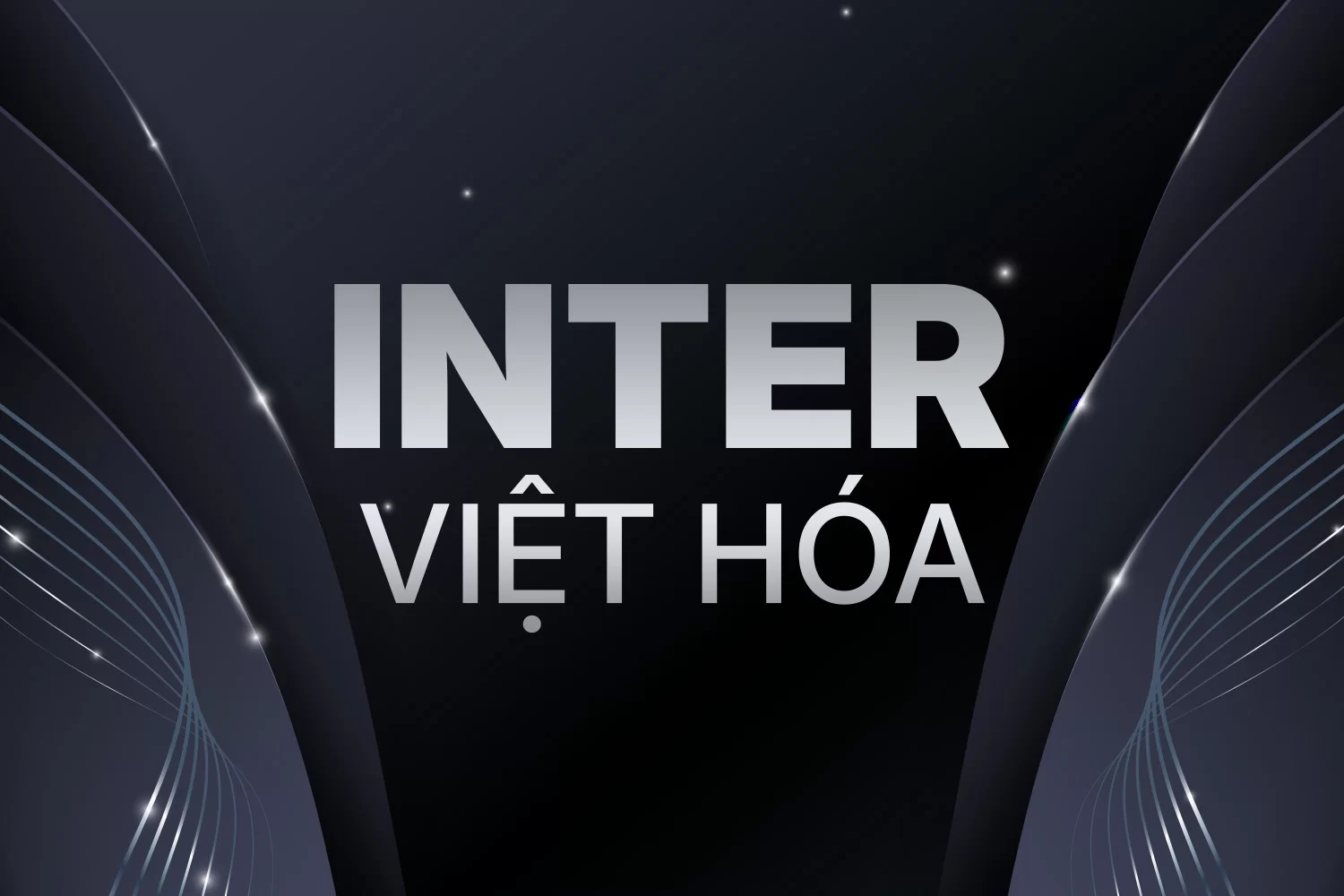
BD StreetSign Sans v2.0 là một font chữ hiện đại được tạo ra bởi Bún Đậu Foundry, lấy cảm hứng từ các bảng hiệu và biển báo đường phố.
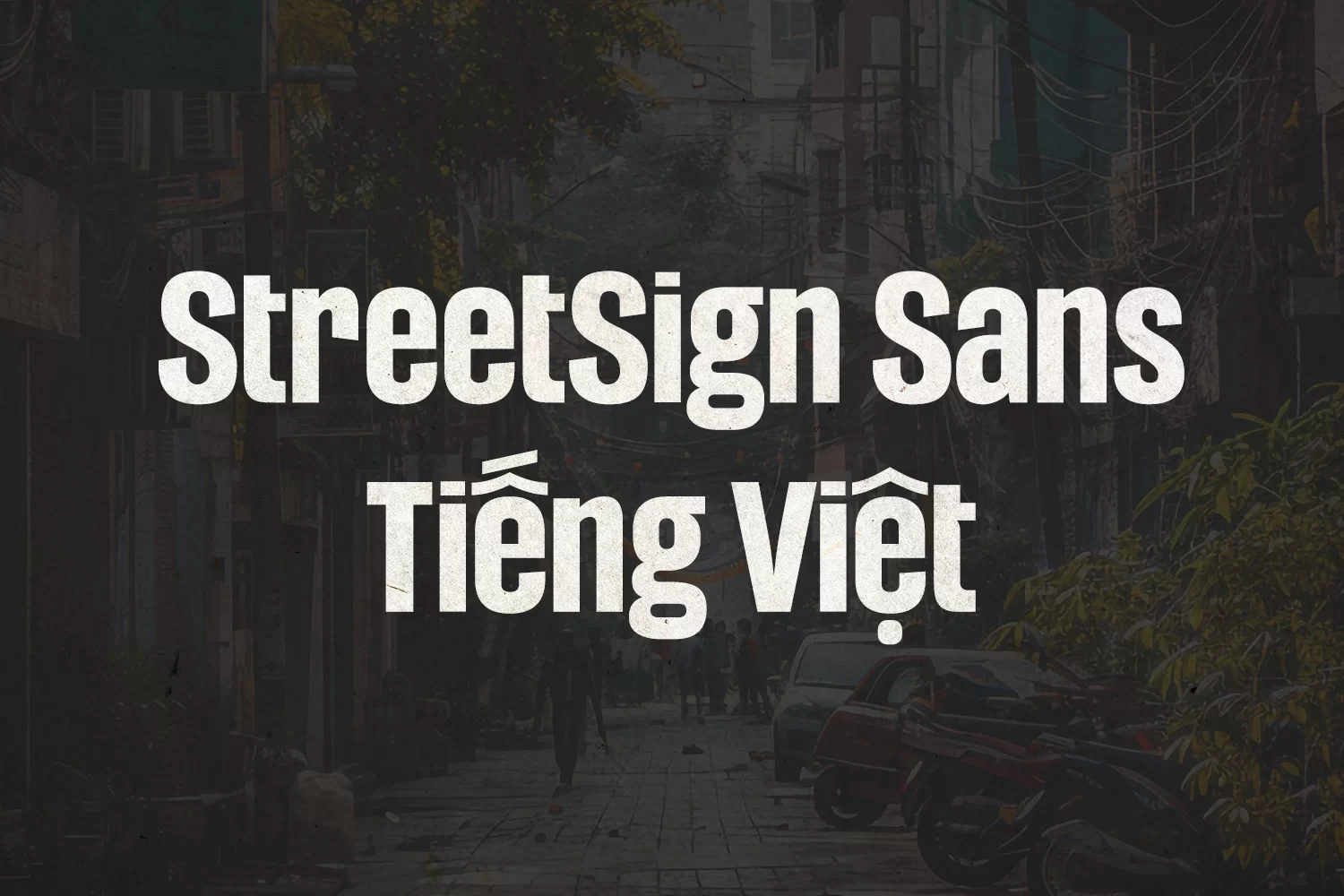
Fraunces là một typeface serif độc đáo kết hợp giữa cảm hứng cổ điển và yếu tố hiện đại, mang lại nét quyến rũ riêng biệt cho mọi thiết kế.
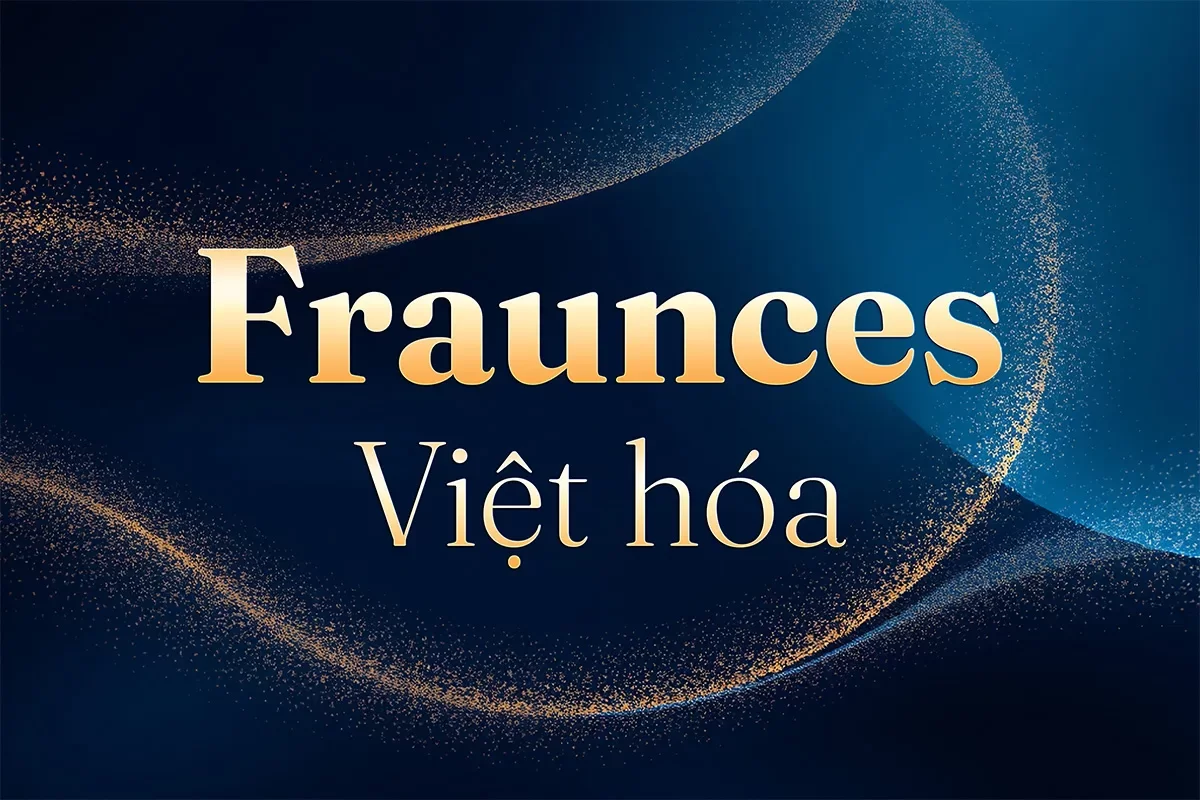
Font Meow Script Việt hóa mang đậm hơi thở của những dòng viết tay mềm mại, uốn lượn một cách duyên dáng như nét cọ trên giấy mịn. Từng ký tự được thiết kế với phong cách tự nhiên, dễ thương, rất phù hợp cho các dự án đòi hỏi cảm xúc nhẹ nhàng và gần gũi.
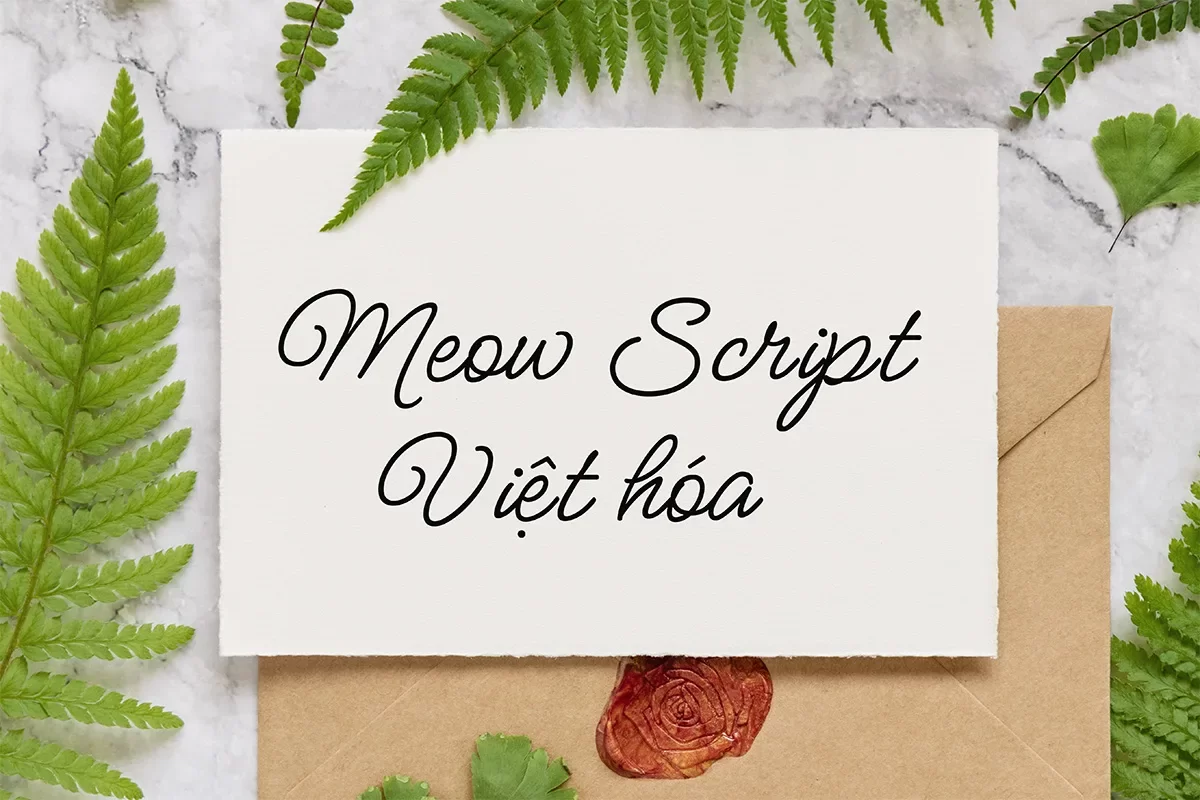
Wind Script Việt hóa là một kiểu chữ bay bổng mang phong cách thư pháp hiện đại, kết hợp giữa sự uyển chuyển tinh tế và độ tương phản mạnh mẽ.
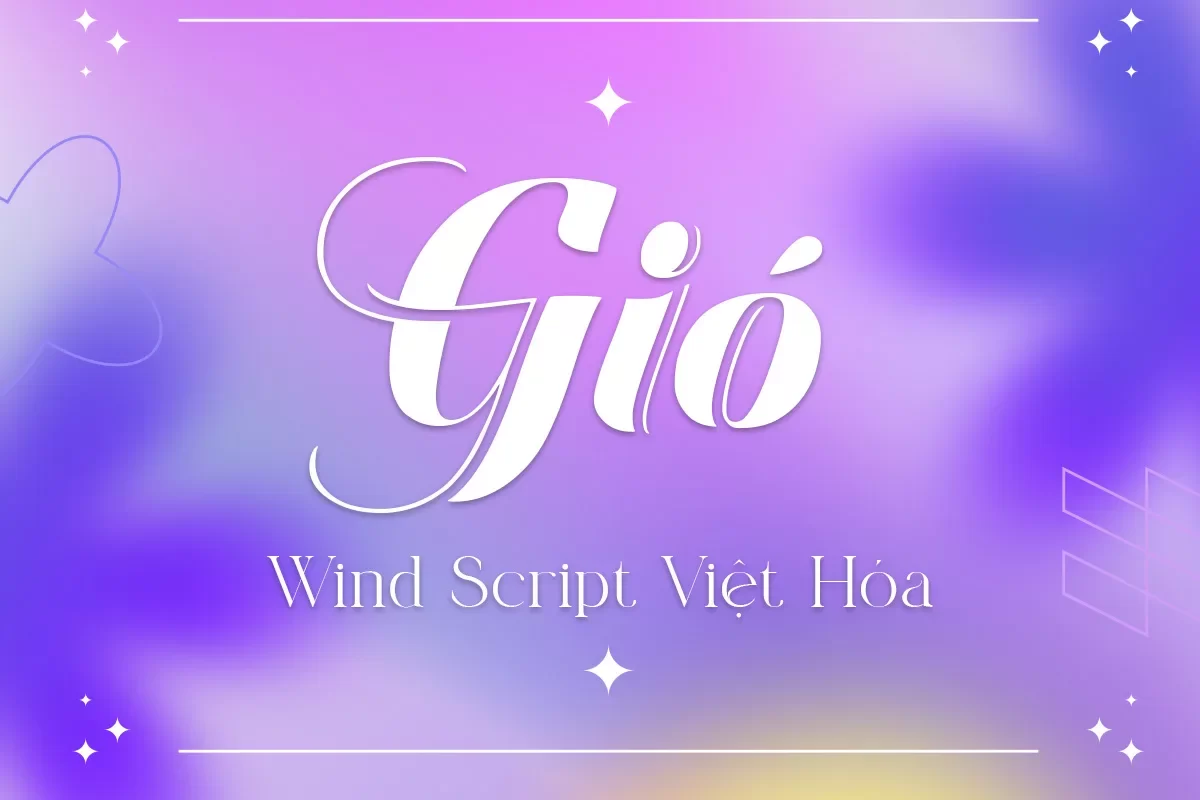
DVN – PoetsenOne Việt hóa là phiên bản Việt hóa của font PoetsenOne nổi bật trên Google Fonts, mang đến một phong cách đậm nét, bo tròn mềm mại và hiện đại. Với cấu trúc chữ cái chắc chắn và đầy đặn, font này truyền tải cảm giác thân thiện, dễ gần nhưng vẫn toát lên sự cá tính và nổi bật trong thiết kế.
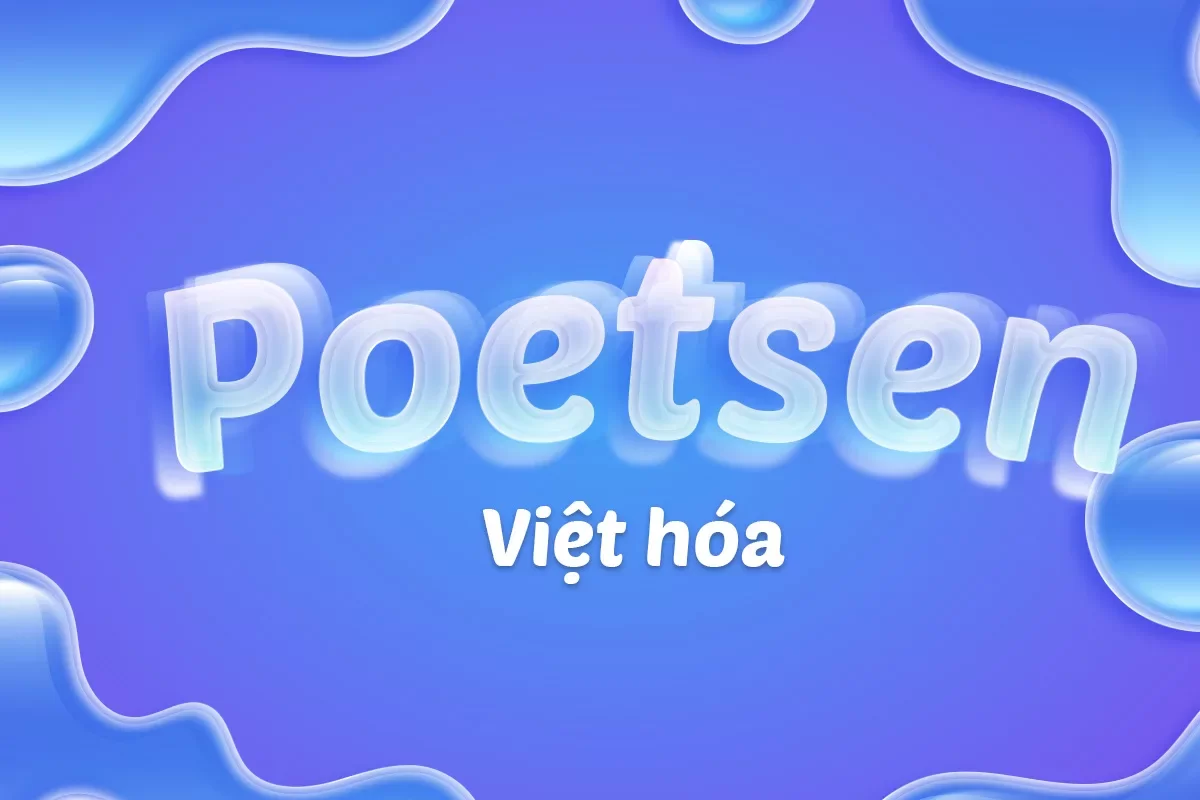
Font Play là một kiểu chữ sans-serif hiện đại, nổi bật với thiết kế tối giản và rõ ràng. Được tạo ra nhằm mang lại trải nghiệm đọc dễ chịu, Play có các đường nét thanh thoát, góc cạnh gọn gàng nhưng vẫn giữ được sự mềm mại ở các chi tiết bo tròn.
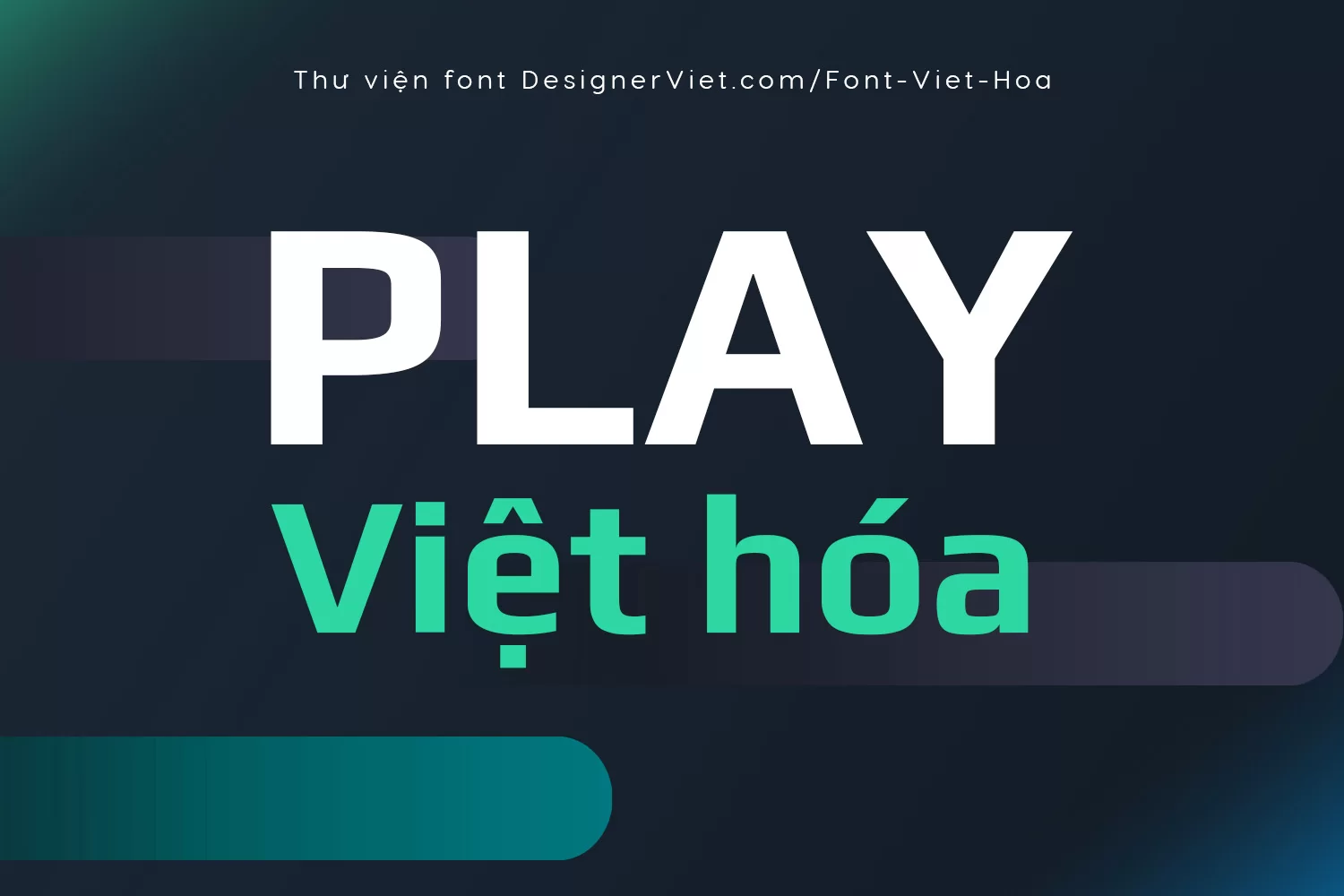
Hubbot Sans là một font chữ sans-serif hiện đại với các đường nét đơn giản và gọn gàng, lý tưởng cho các dự án cần sự rõ ràng và dễ đọc.
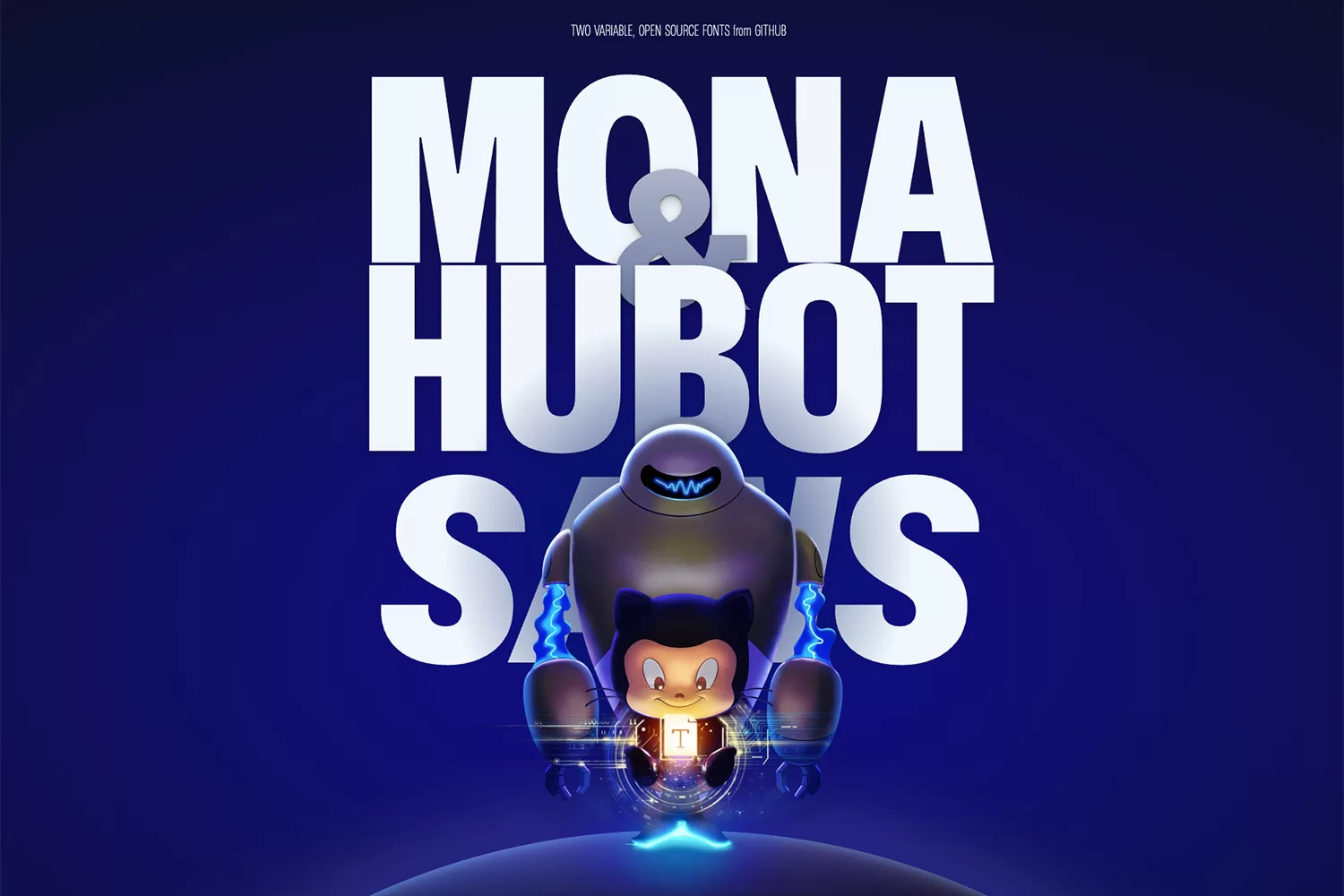
DVN Easter là một font chữ mang phong cách vui nhộn, sáng tạo, được thiết kế lấy cảm hứng từ những quả trứng phục sinh rực rỡ. Với các ký tự bo tròn, đáng yêu và các họa tiết trang trí bên trong, font này giúp bạn dễ dàng tạo ra những thiết kế ấn tượng cho các dự án lễ hội.
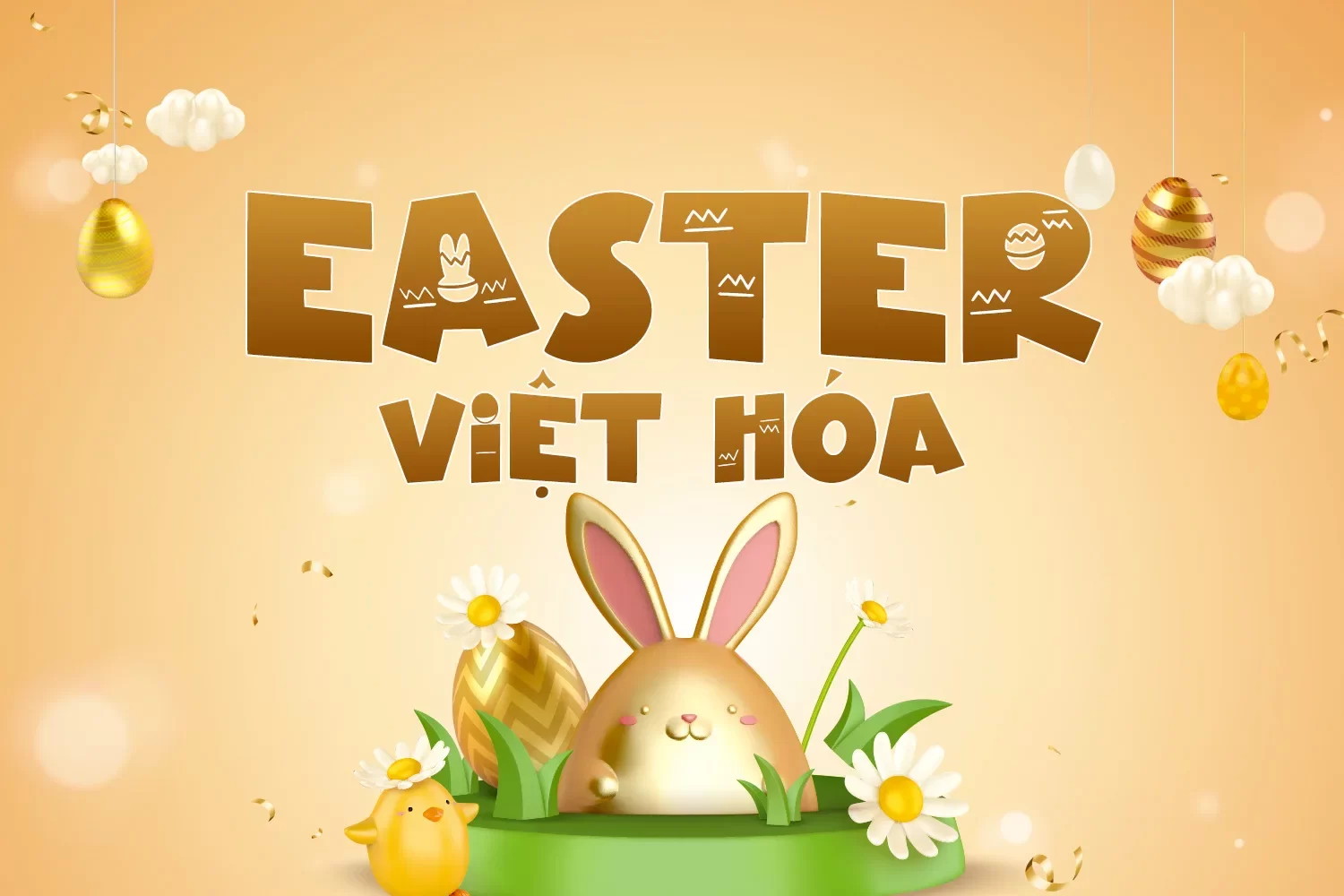
Fredoka One là một phông chữ được thiết kế bởi Atipo, một hãng thiết kế đồ họa đặt trụ sở tại Tây Ban Nha. Nó có phong cách đơn giản, vui nhộn và thân thiện, thích hợp cho việc sử dụng trong các dự án sáng tạo và giao diện người dùng.
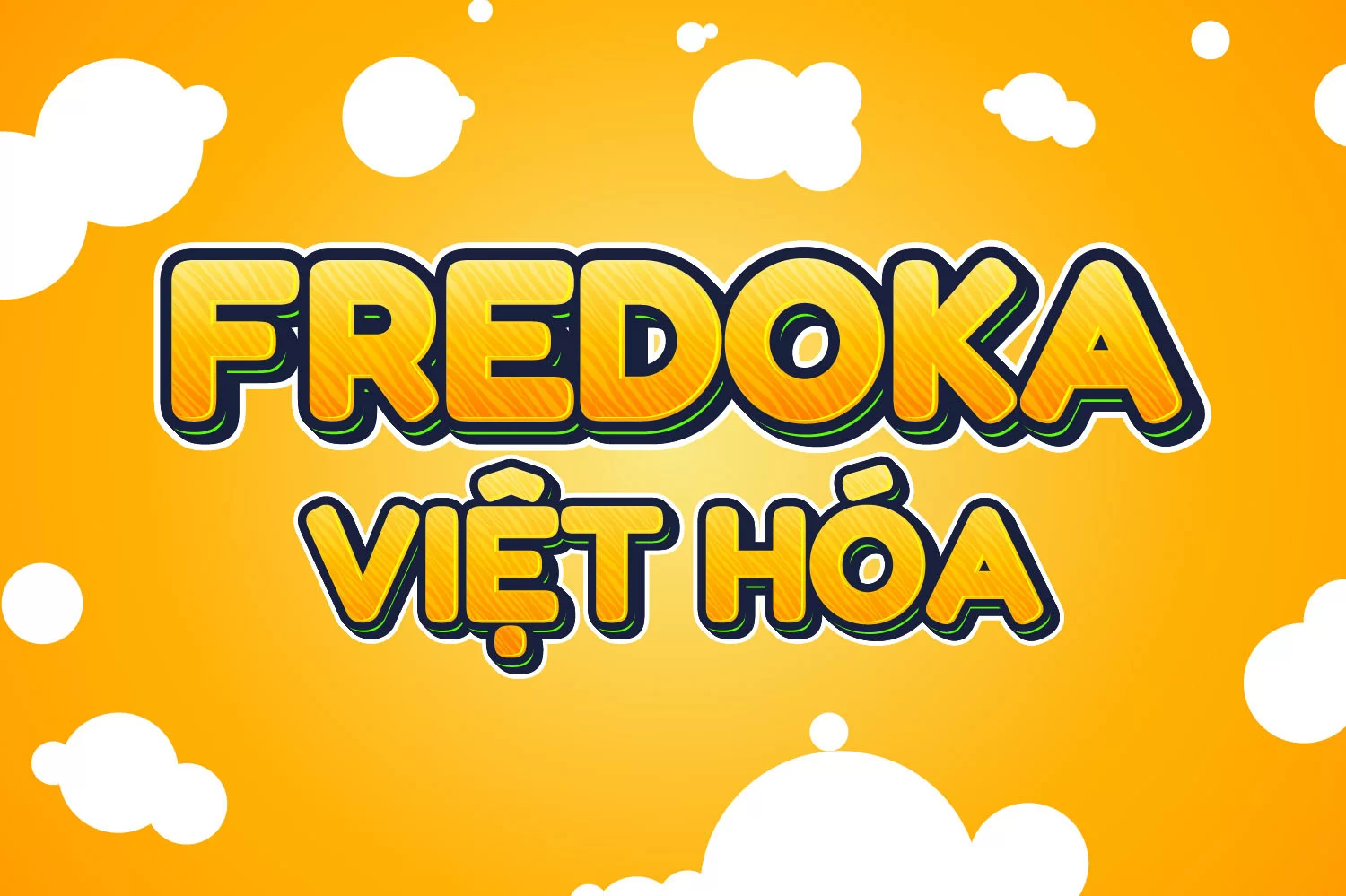
1. Font Inter Việt hóa
Inter là một bộ font sans-serif miễn phí, được phát triển bởi Rasmus Andersson nhằm tối ưu hóa việc hiển thị trên màn hình.
2. Font BD StreetSign Sans (Việt hóa)
BD StreetSign Sans v2.0 là một font chữ hiện đại được tạo ra bởi Bún Đậu Foundry, lấy cảm hứng từ các bảng hiệu và biển báo đường phố.
3. Font Fraunces (Việt hóa)
Fraunces là một typeface serif độc đáo kết hợp giữa cảm hứng cổ điển và yếu tố hiện đại, mang lại nét quyến rũ riêng biệt cho mọi thiết kế.
4. Font Meow Script (Việt hóa)
Font Meow Script Việt hóa mang đậm hơi thở của những dòng viết tay mềm mại, uốn lượn một cách duyên dáng như nét cọ trên giấy mịn. Từng ký tự được thiết kế với phong cách tự nhiên, dễ thương, rất phù hợp cho các dự án đòi hỏi cảm xúc nhẹ nhàng và gần gũi.
5. Font Wind Script (Việt hóa)
Wind Script Việt hóa là một kiểu chữ bay bổng mang phong cách thư pháp hiện đại, kết hợp giữa sự uyển chuyển tinh tế và độ tương phản mạnh mẽ.
6. Font PoetsenOne (Việt hóa)
DVN – PoetsenOne Việt hóa là phiên bản Việt hóa của font PoetsenOne nổi bật trên Google Fonts, mang đến một phong cách đậm nét, bo tròn mềm mại và hiện đại. Với cấu trúc chữ cái chắc chắn và đầy đặn, font này truyền tải cảm giác thân thiện, dễ gần nhưng vẫn toát lên sự cá tính và nổi bật trong thiết kế.
7. Font Play (Việt hóa)
Font Play là một kiểu chữ sans-serif hiện đại, nổi bật với thiết kế tối giản và rõ ràng. Được tạo ra nhằm mang lại trải nghiệm đọc dễ chịu, Play có các đường nét thanh thoát, góc cạnh gọn gàng nhưng vẫn giữ được sự mềm mại ở các chi tiết bo tròn.
8. Trọn bộ Font Hubot Sans (Việt hóa)
Hubbot Sans là một font chữ sans-serif hiện đại với các đường nét đơn giản và gọn gàng, lý tưởng cho các dự án cần sự rõ ràng và dễ đọc.
9. Font Easter (Việt hóa)
DVN Easter là một font chữ mang phong cách vui nhộn, sáng tạo, được thiết kế lấy cảm hứng từ những quả trứng phục sinh rực rỡ. Với các ký tự bo tròn, đáng yêu và các họa tiết trang trí bên trong, font này giúp bạn dễ dàng tạo ra những thiết kế ấn tượng cho các dự án lễ hội.
10. Font Fredoka (Việt hóa)
Fredoka One là một phông chữ được thiết kế bởi Atipo, một hãng thiết kế đồ họa đặt trụ sở tại Tây Ban Nha. Nó có phong cách đơn giản, vui nhộn và thân thiện, thích hợp cho việc sử dụng trong các dự án sáng tạo và giao diện người dùng.
Gợi ý sử dụng:
- Thiết kế giao diện/website: Inter, Play, Hubot Sans
- Poster, tiêu đề, biển hiệu: BD StreetSign Sans, Fraunces
- Thiệp mời, thiết kế nữ tính: Meow Script, Wind Script
- Thiết kế vui tươi, sáng tạo: PoetsenOne, Fredoka, Easter